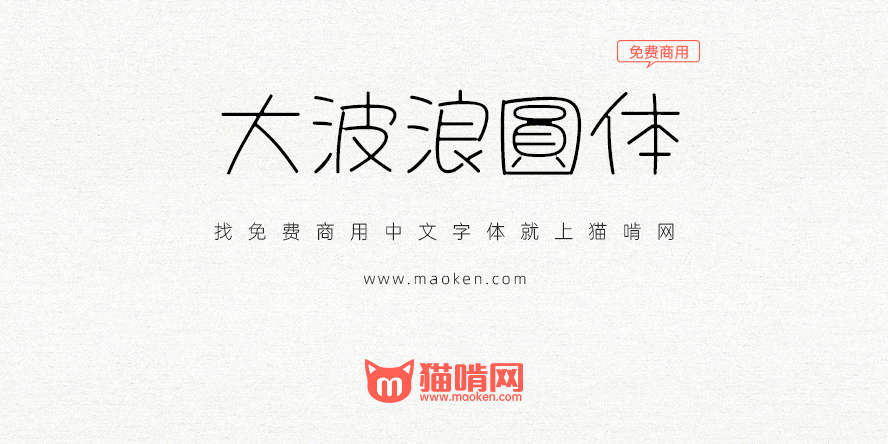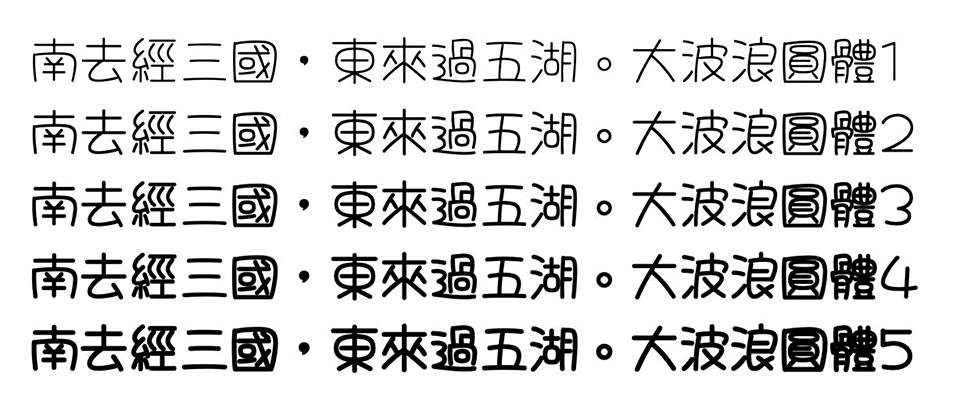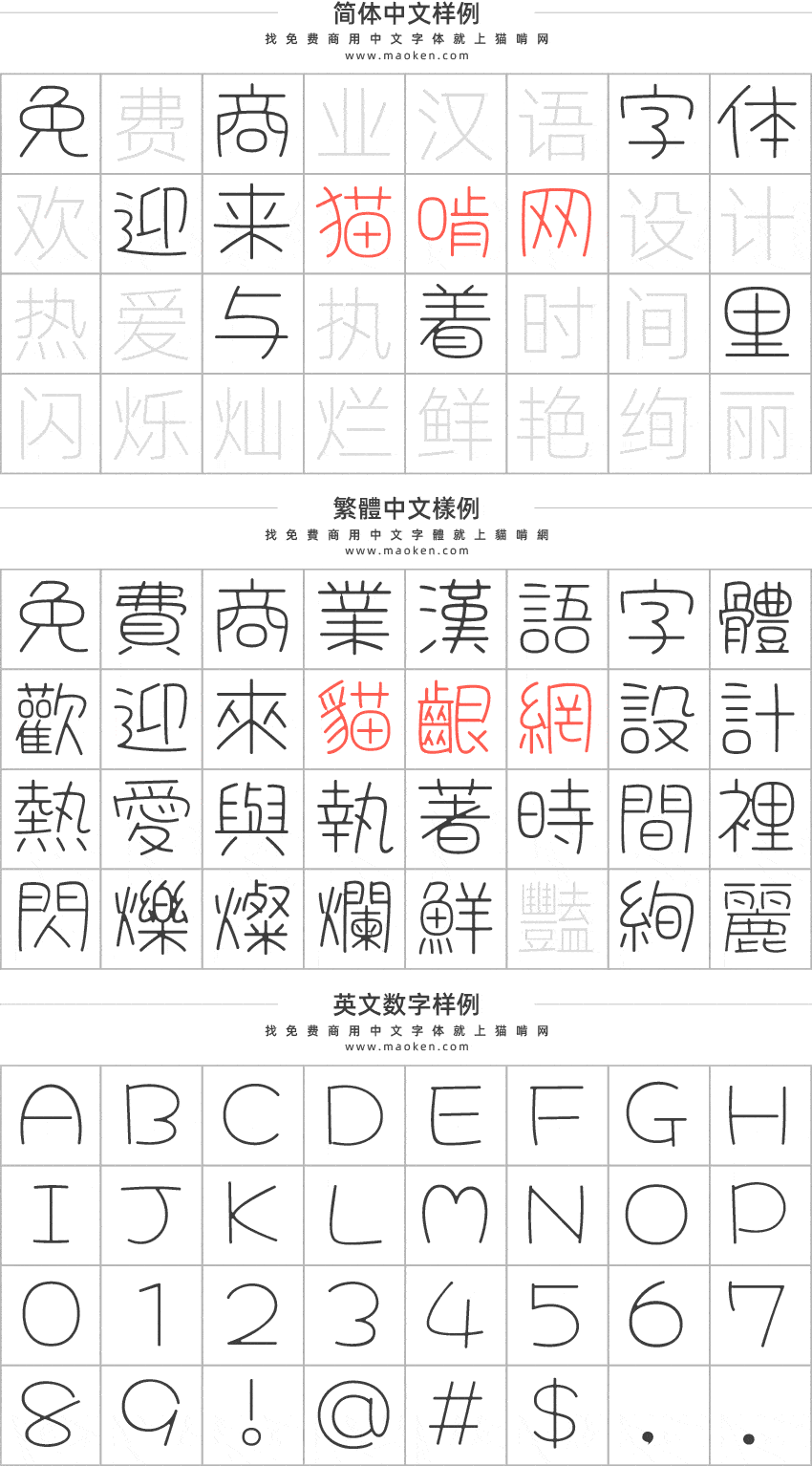
大波浪圆体是八丸POP体(はちまるポップ)字体的补字计划。与原作者的主要差异是调整部件写法、新增中文字、增加为5个字重、增加一些符号。可以免费商用,欢迎大家自由应用、自由优化、自由改作!
特色1:弥补繁体中文常用字缺字缺憾
目前缓慢地补字中…,每天增加几个字,第一阶段是要完成4800个台湾常用字,目前版本 ver 1.000版,还没有补完!
目前 ver 1.000版 CJK TC 与原作者,新增了826字。
1、由于是非专业级的补字,新加入的字在风格上,虽然尽力求一致,难免会与原作者会有一些不同或较丑。
2、原作者的部件是使用日本写法,补的字目前是使用台标体,混搭起来有时候会怪怪的,聊胜于无。
特色2:5种字重(Style)
原作者的字重放在Regular字重裡,透过程序自动产生Light、DemiLight、SemiBold、Bold 新的字重。
在ExtraLight和Light字重是把原作者Regular字重微微调细一点点。在Light的字重裡,可能会因为笔划太细造成某些笔画消失。
在SemiBold与Bold的字重裡,可能会因为笔划太粗造成某些笔画重叠难以识别,有粗体字的需求,可以先挑战使用Bold字重看看,如果发现效果不如预期,再改用SemiBold字重。
不能确定自动产生出来的字重裡每一个都是完整的字,毕尽程序会误判是常有的事情,所以“不是在Regular字重”裡的笔划可能会消失。
特色3:调整标点符号位置
原作者的全形标点符号针对日本做设计,调整为台湾常见的置中用法。
特色4:增加台湾闽南语和客语的部份中文字
中文字如下:
特色5:调整部件写法
相同一个字,在不地区的书写方式可能会略有不同,原作者的字都放 CJK JP的字型档案里。